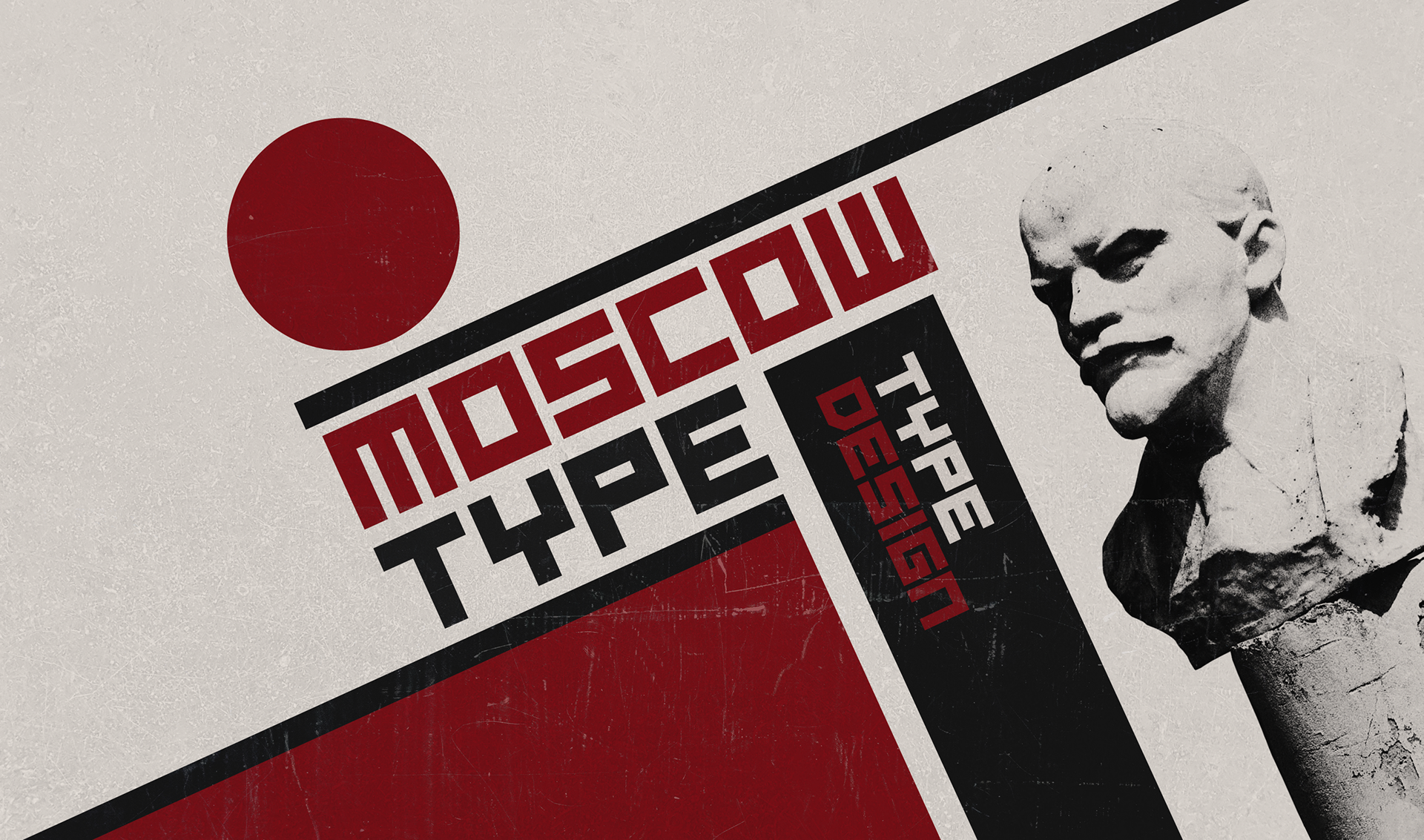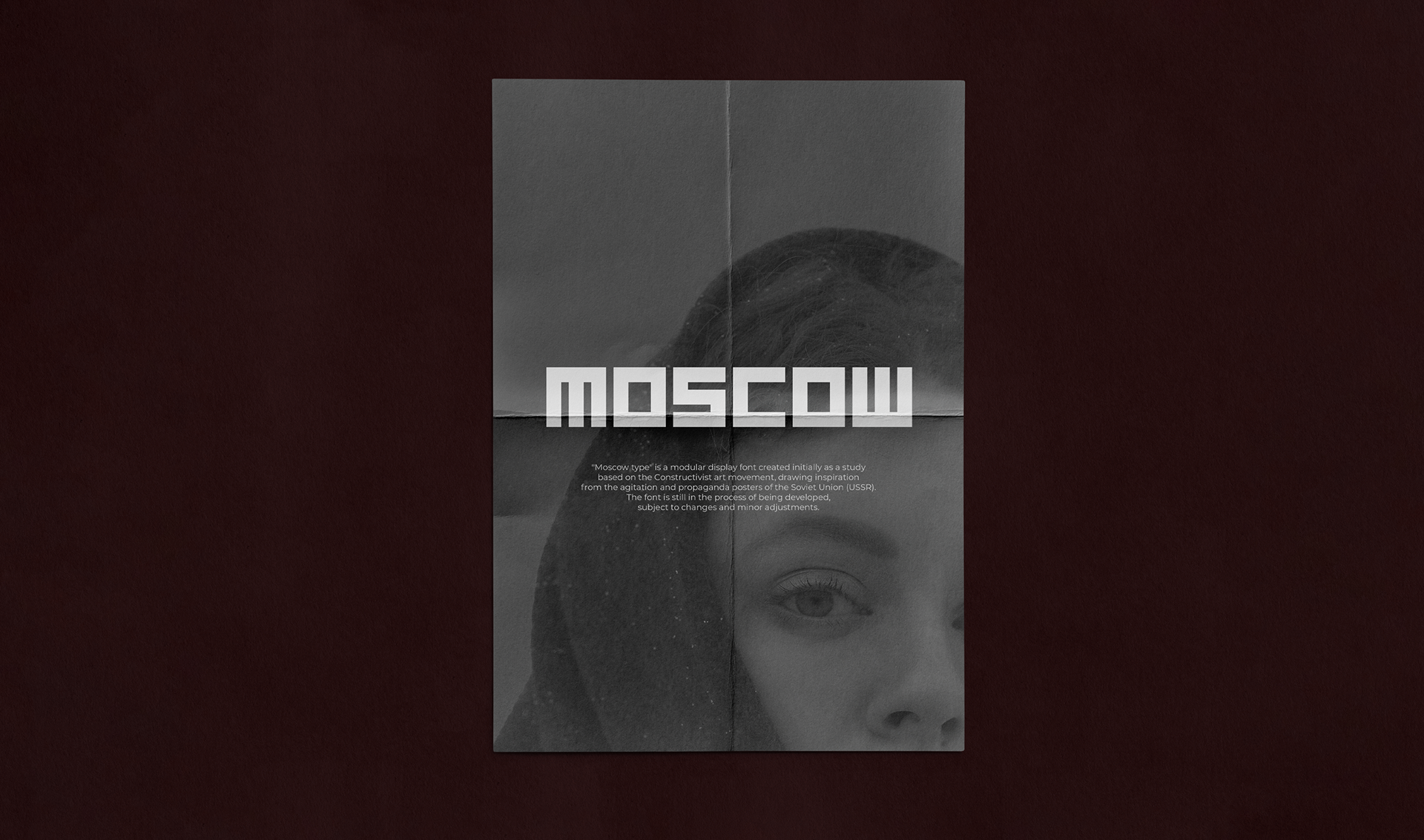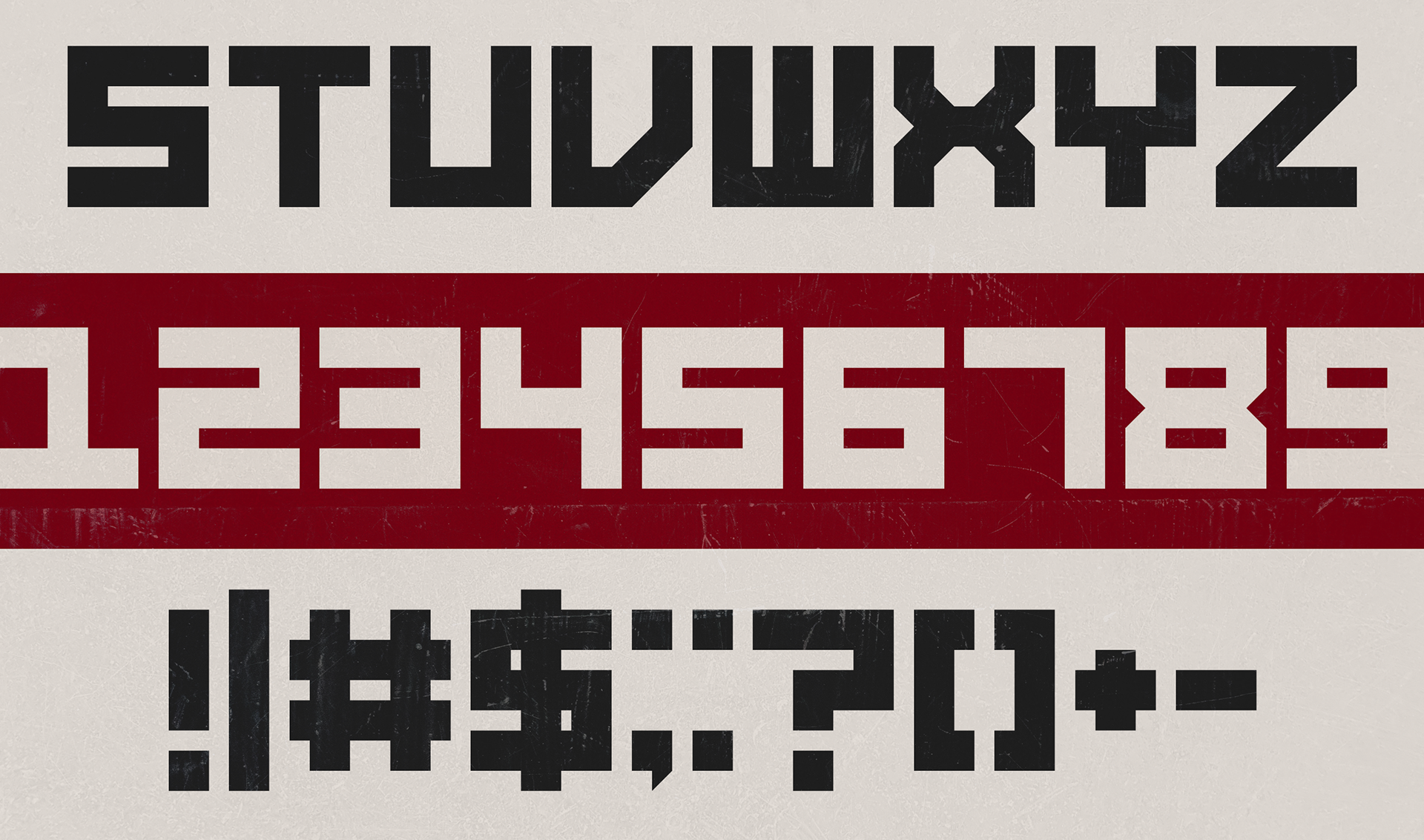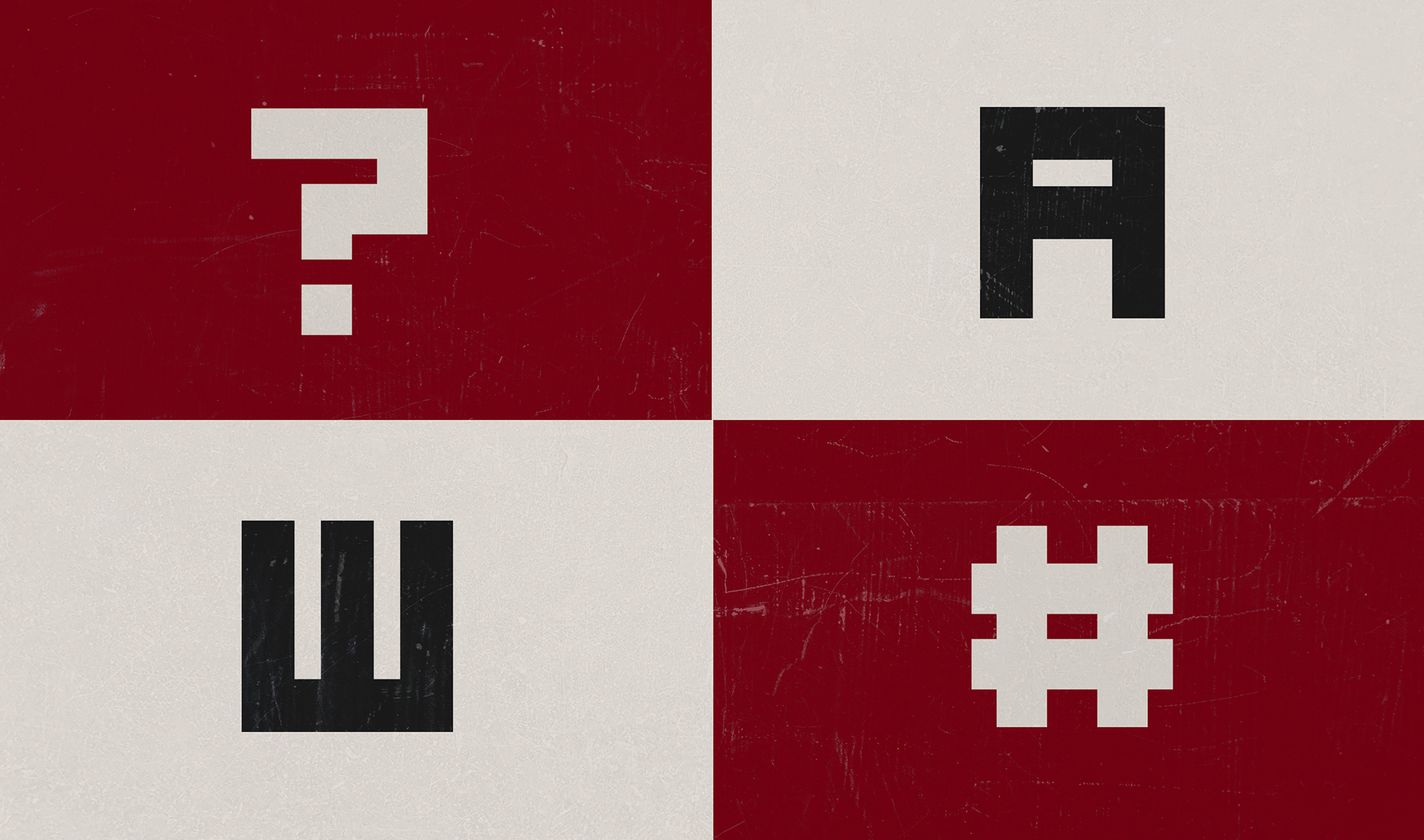
Moscow Type
"Moscow type" é uma fonte display modular criada inicialmente como um estudo baseado no movimento artístico construtivista, utilizando como referência os cartazes de agitação e propaganda da União Soviética (URSS). A fonte ainda está em processo de criação, sendo sujeita a alterações e pequenos ajustes.
"Moscow type" is a modular display font created initially as a study based on the Constructivist art movement, drawing inspiration from the agitation and propaganda posters of the Soviet Union (USSR). The font is still in the process of being developed, subject to changes and minor adjustments.